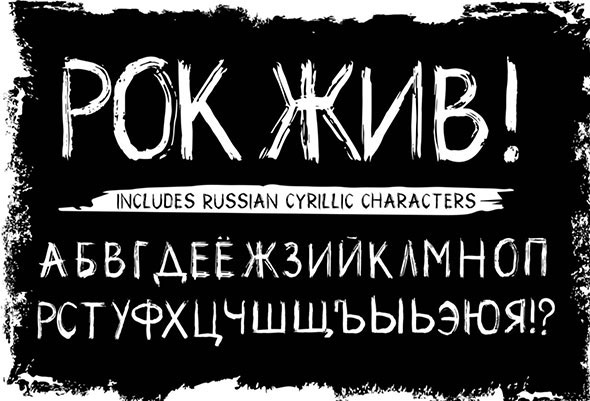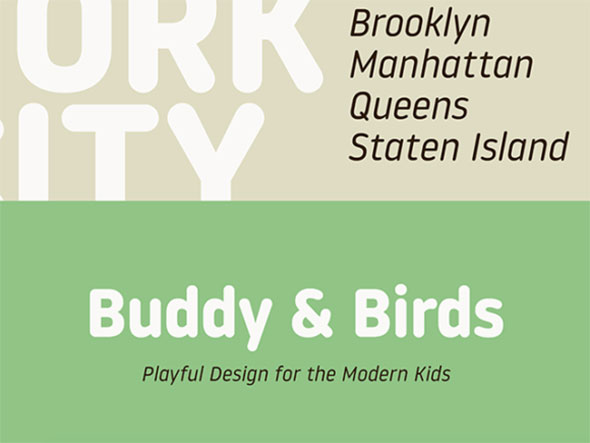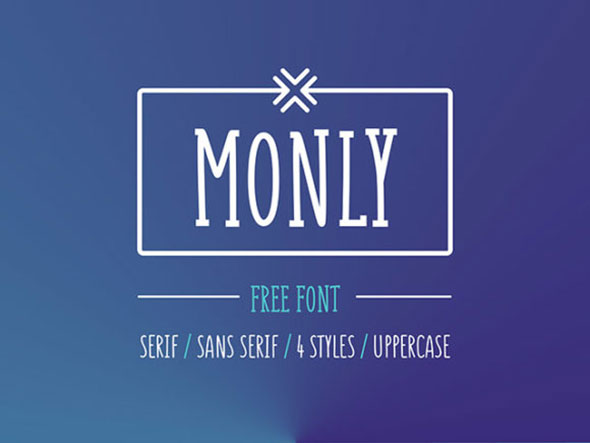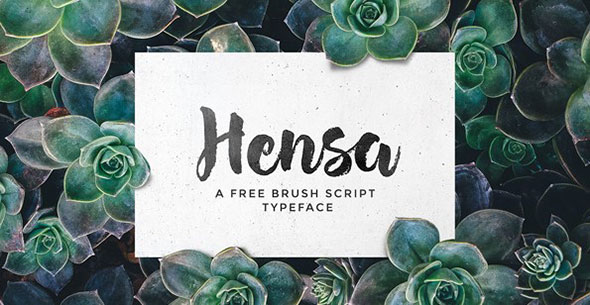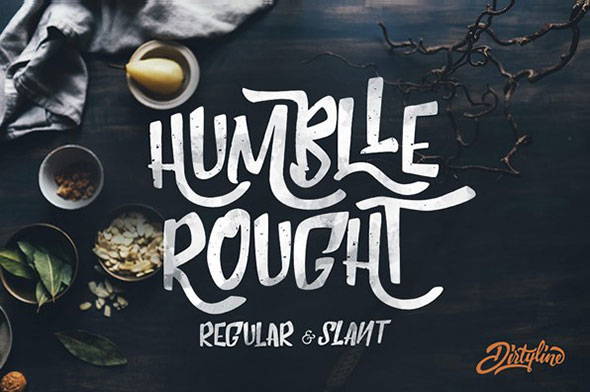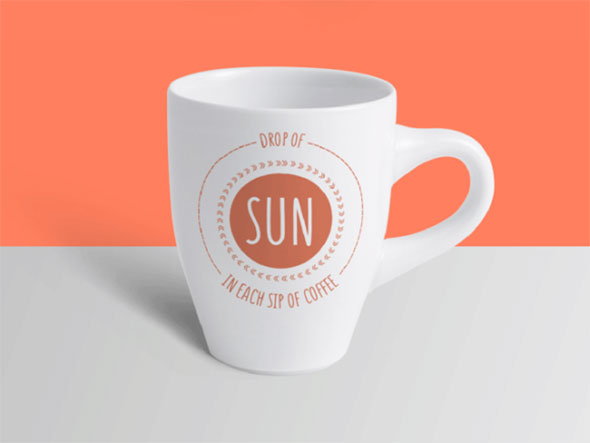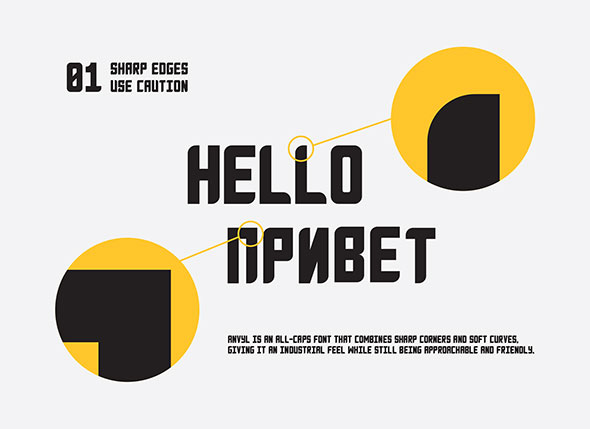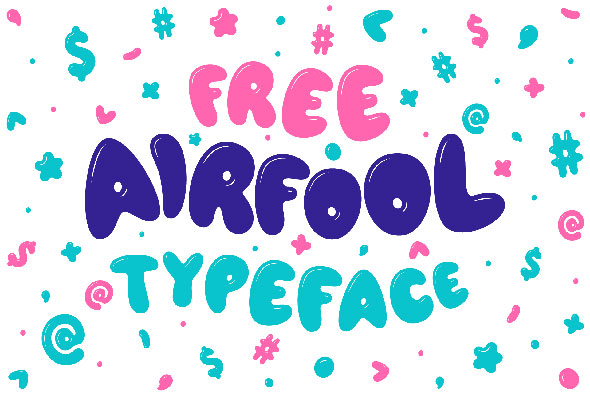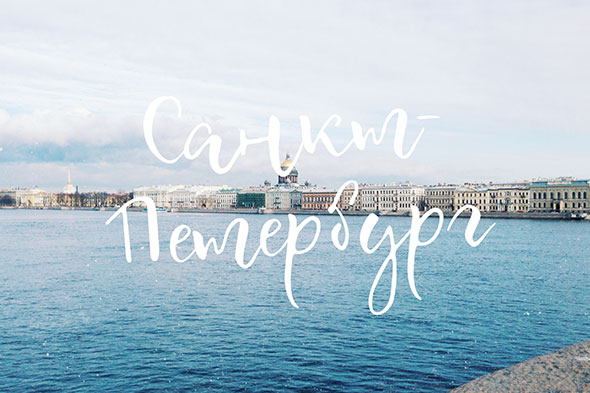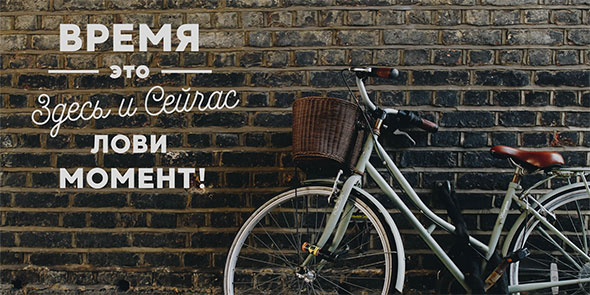
Бесплатные шрифты с игривым настрением
Весна уже фактически пришла, и лето не за горами! Это период ярких дизайн-проектов с легким, веселым настроением. Мы собрали бесплатные шрифты, которые помогут вам в оформлении таких работ. Вы найдете бесплатные кириллические и латинские шрифты.
Кириллица
Drum
ANVYL
AIRFOOL
TheArtist
Kurocka Lapkoi
Celestina
GoodTime
Shnobel
Латиница
Metafors
Noway Round
Banaue
Monly
Smooth Stone
Hensa
Humblle Rought
SUNN